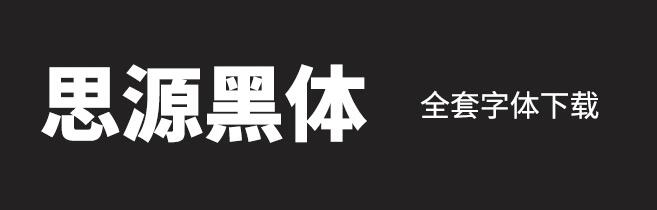
思源字体,人人必备字体之一。
思源黑体是Adobe与Google宣布推出的一款开源字体,有七种字体粗细(ExtraLight、Light、Normal、Regular、Medium、Bold 和 Heavy),完全支持日文、韩文、繁体中文和简体中文,还包括来自 Source Sans 字体家族的拉丁文、希腊文和西里尔文字形共65536个字形。
Google将其命名为Noto Sans JK,作为 Google 的 Noto 字体家族的成员。
Adobe 则命名为 Source Han Sans,作为 Adobe 的 Source 字体家族的一员。
Noto Sans CJK 的风格介于现代和传统之间。设计目标是可以广泛用于多种用途的计算机字体,比如用于手机、平板、或者桌面的用户界面、网页浏览或者电子书阅读等等。